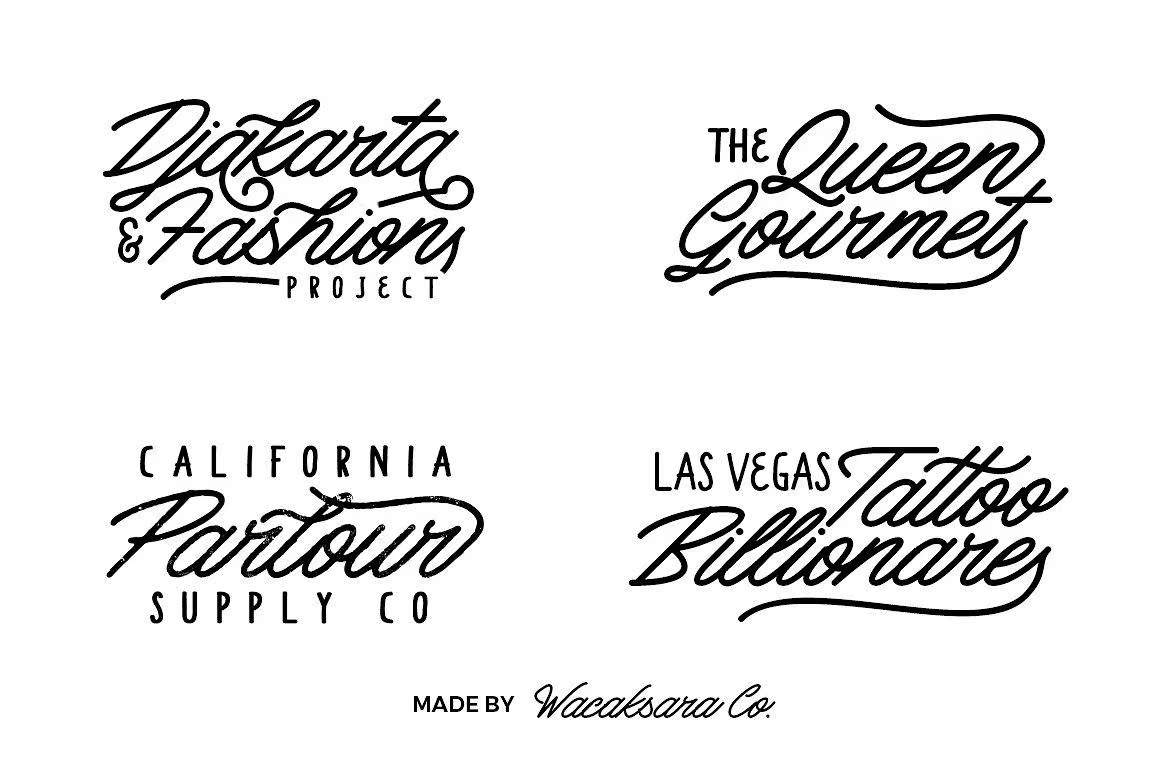
Afve-FontFamily由三个描述和两个All capssans组成,Mattcoolisa VintageMonol字体,具有完美的自然流。它是个人品牌项目、手写报价、产品包装的完美选择,或是作为时尚现代的背景图像外覆使用。Afve-FontFamily由三个描述和两个All-capssans组成,MattCool是一款具有自然流量的VintageMonoline字体。它是个人品牌项目、手写报价单、产品包装的完美选择,或是作为时尚现代的背景图像外接使用。